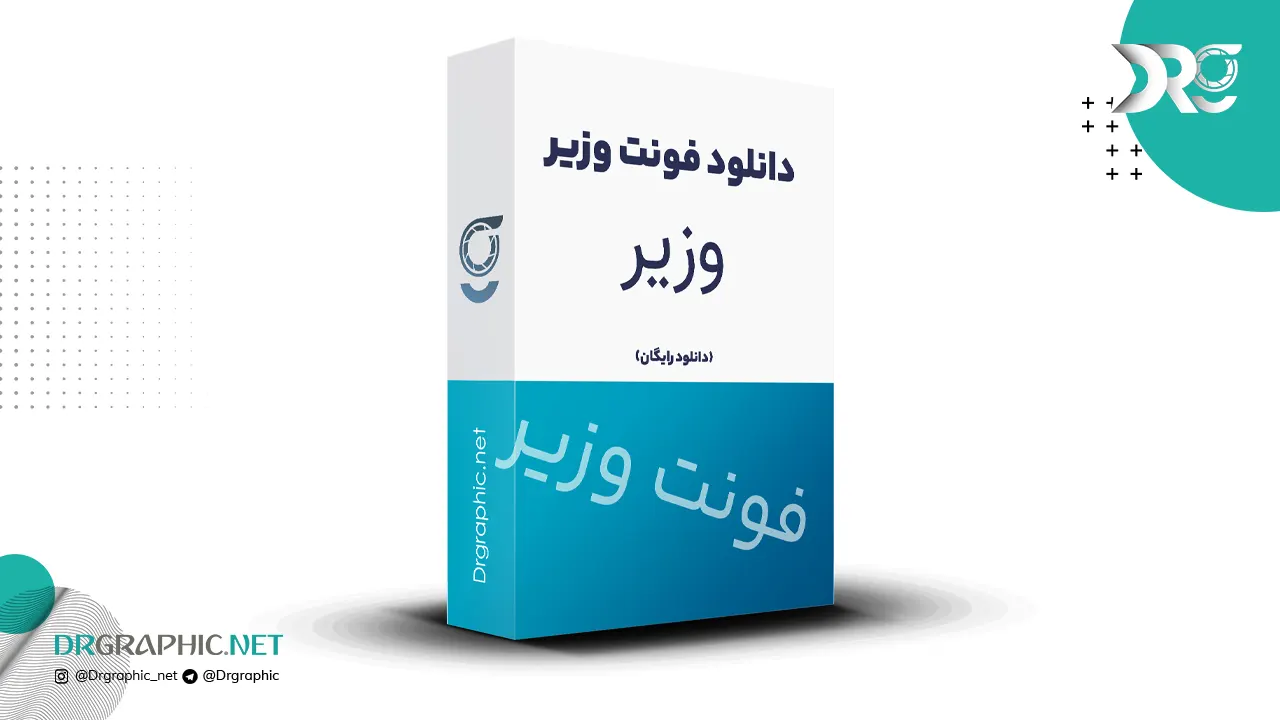
فونت وزیر VAZIR
• مناسب برای فونت سایت
• مناسب برای نامه نگاری
فونت وزیر از سری فونت های سنس سریف است و به همین دلیل فونتی است برای استفاده در صفحات وب، رابط کاربری برنامه‌ها و در کل هر کجا که نیاز باشد نوشته ها در صفحه نمایش به تصویر در آیند . فونت فارسی وزیر باز طراحی فونت DejaVu می باشد و خیلی از ویژگیهای بصری را از این فونت به ارث برده است.
نکته قایل توجه در مورد فونت وزیر کیفیت بالای آن به همراه طیف گسترده اوزان این فونت میباشد ،این فونت در وزن های خیلی نازک ، نازک ، معمولی ، کمی ضخیم و ضخیم در دسترس است که با دانلود این فونت میتوانید به کلیه وزن های نام برده شده دسترسی داشته باشید. با دکتر گرافیک همراه باشید.
طراح این فونت آقای صابر راستی‌کردار  است که یکی از اعضای فعال جامعهٔ نرم‌افزار آزاد و متن‌باز بود. او متولد بندرعباس بود و در شیراز بزرگ شد. فونت‌های مهم راستی‌کردار، شامل وزیرمتن می‌شود که در نسخهٔ فارسی نرم‌افزار پیام‌رسان تلگرام استفاده شده‌است. او در ۳۶ سالگی بر اثر ابتلا به سرطان ریه درگذشت.